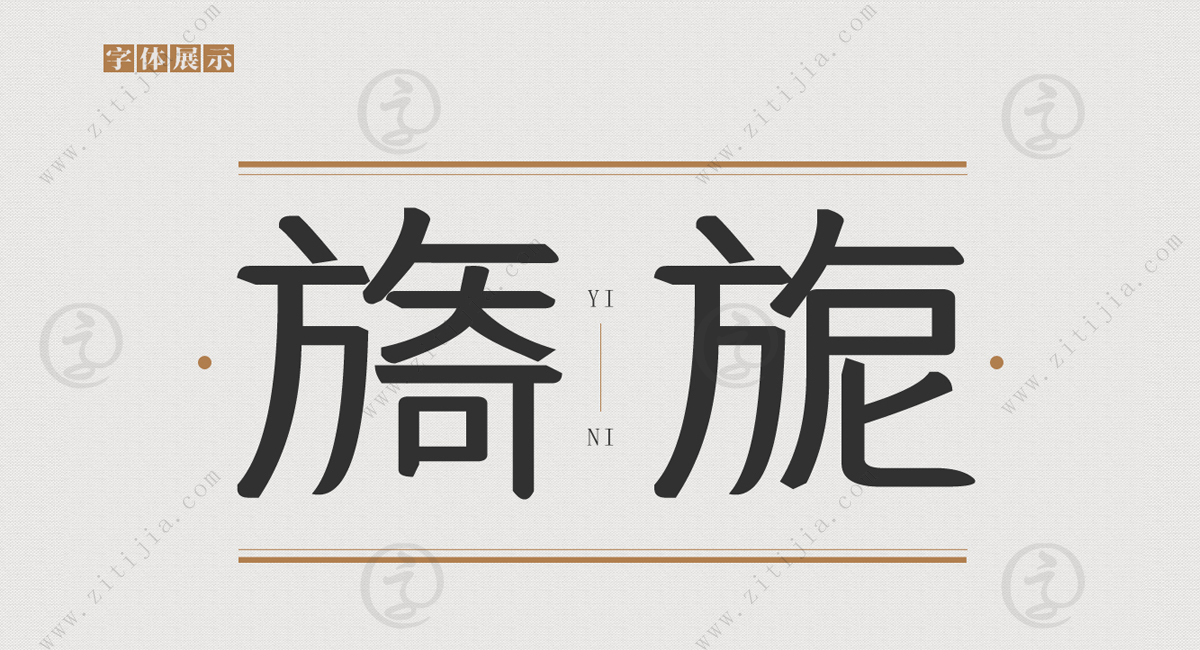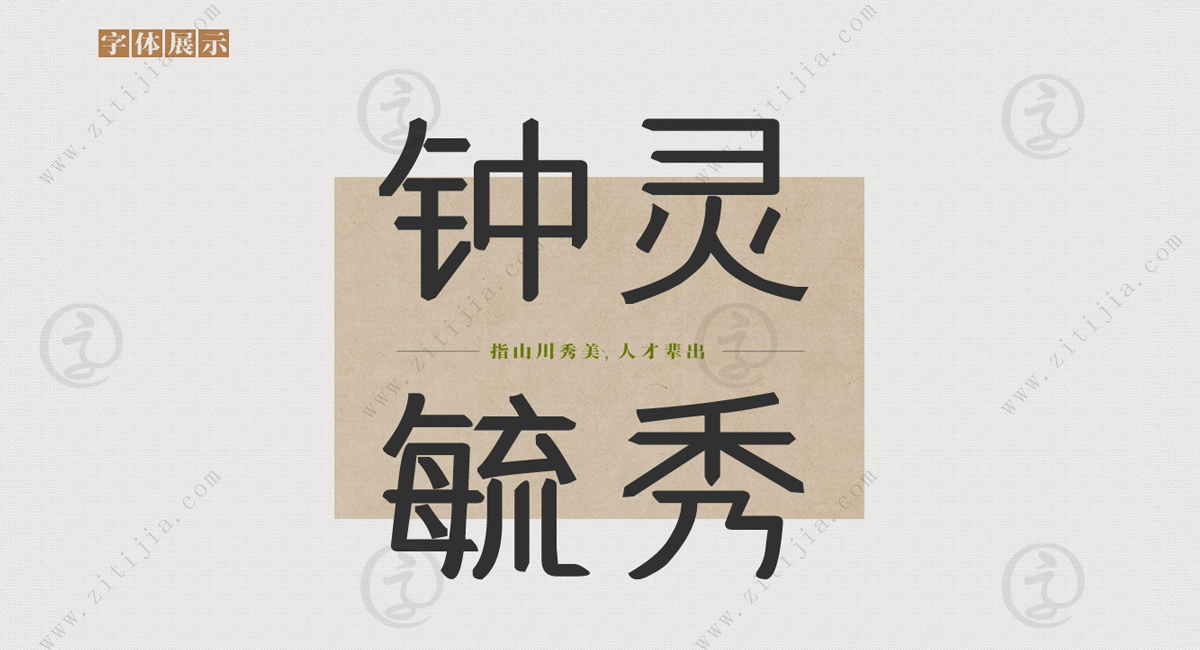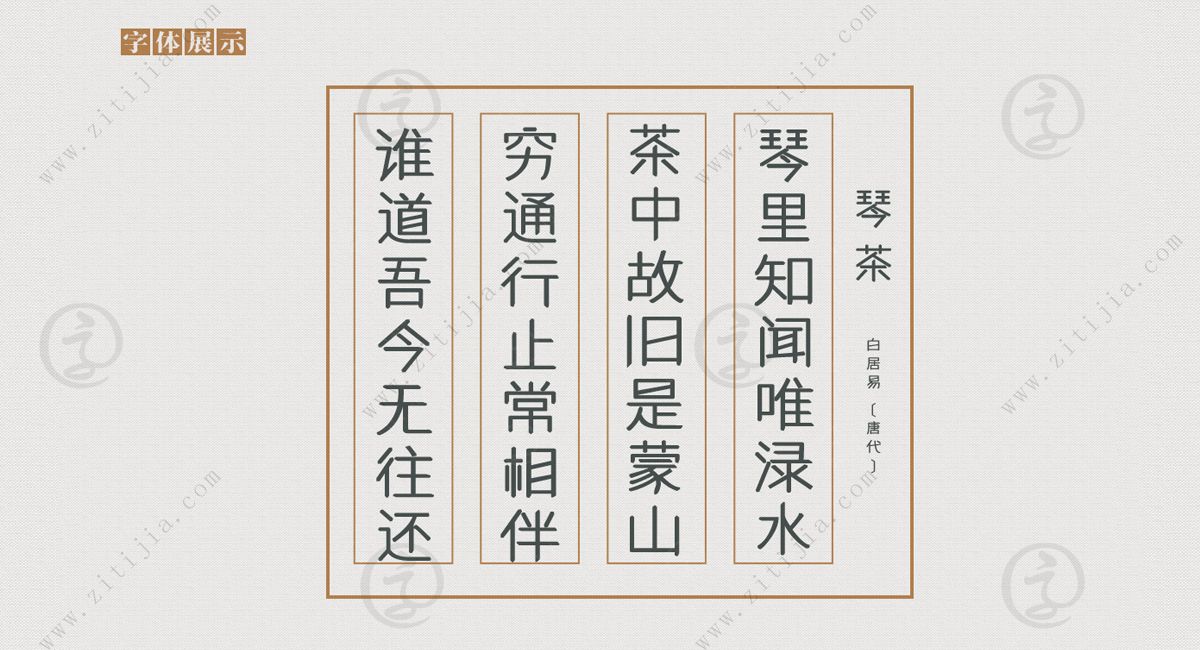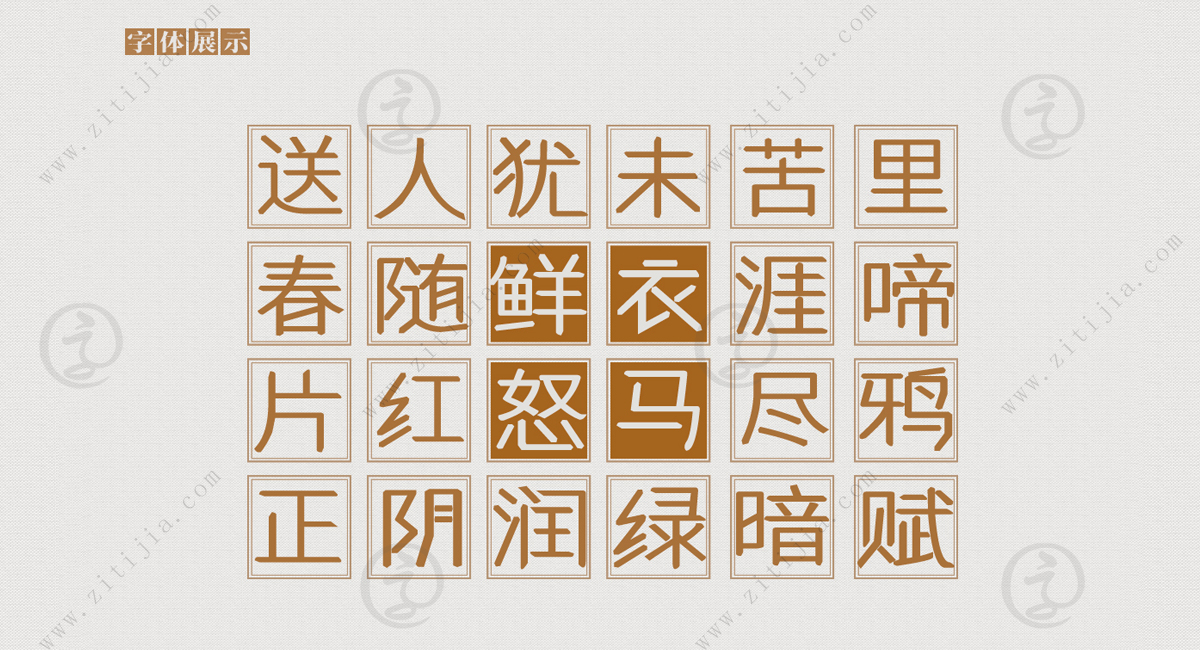
南构望朝歌字体│带给我们一种宁静和沉思的氛围
南构望朝歌字体,一款令人陶醉的艺术字体,如同一位独特的舞者,在纸上舞动着优美的姿态。它的笔画横平竖直,每一划都显得圆劲均匀,粗细一致,展现出一种独特的美感与力量。
这款字体由南构字库创意设计发行,是对五千年来中华汉字精华的沉淀与传承。它汲取了中华文化的精髓,融合了传统与现代的元素,将汉字的结构演绎到极致。字体的结构刚正不阿,每一笔都显得坚实而丰满,给人一种稳重而有力的感觉。
南构望朝歌字体的设计师们对每一个笔画都进行了精雕细琢,追求极致的完美。他们注重每一笔的力度和节奏,使得每个字体都充满了生命力和动感。无论是书写还是印刷,这款字体都能展现出独特的美学价值。
南构望朝歌字体的特点不仅在于其优雅的外观,更重要的是它所传递的文化内涵。它承载着中华文明的历史与传统,体现了文化的底蕴和深度。每一个字体都仿佛是一个故事,让人们在书写中感受到历史的厚重和情感的流转。
无论是书法爱好者还是设计师,南构望朝歌字体都是一种难以抗拒的魅力。它的优雅和独特性使得它成为各种艺术作品的理想选择,无论是书法作品、广告设计还是品牌标识,它都能为作品增添独特的艺术气息。
南构望朝歌字体的问世,不仅仅是一种字体的创作,更是对中华文化的传承与发展的见证。它以其独特的风格和内涵,成为了中华文化的一部分,展现了中华民族的智慧和创造力。
在这个快节奏的时代,南构望朝歌字体带给我们一种宁静和沉思的氛围。它让人们重新审视汉字的美丽和力量,感受到传统与现代的交融。无论是书写还是欣赏,南构望朝歌字体都能带给人们一种独特的艺术享受,让我们在灯火阑珊处,寻找到心灵的归宿。
南构望朝歌